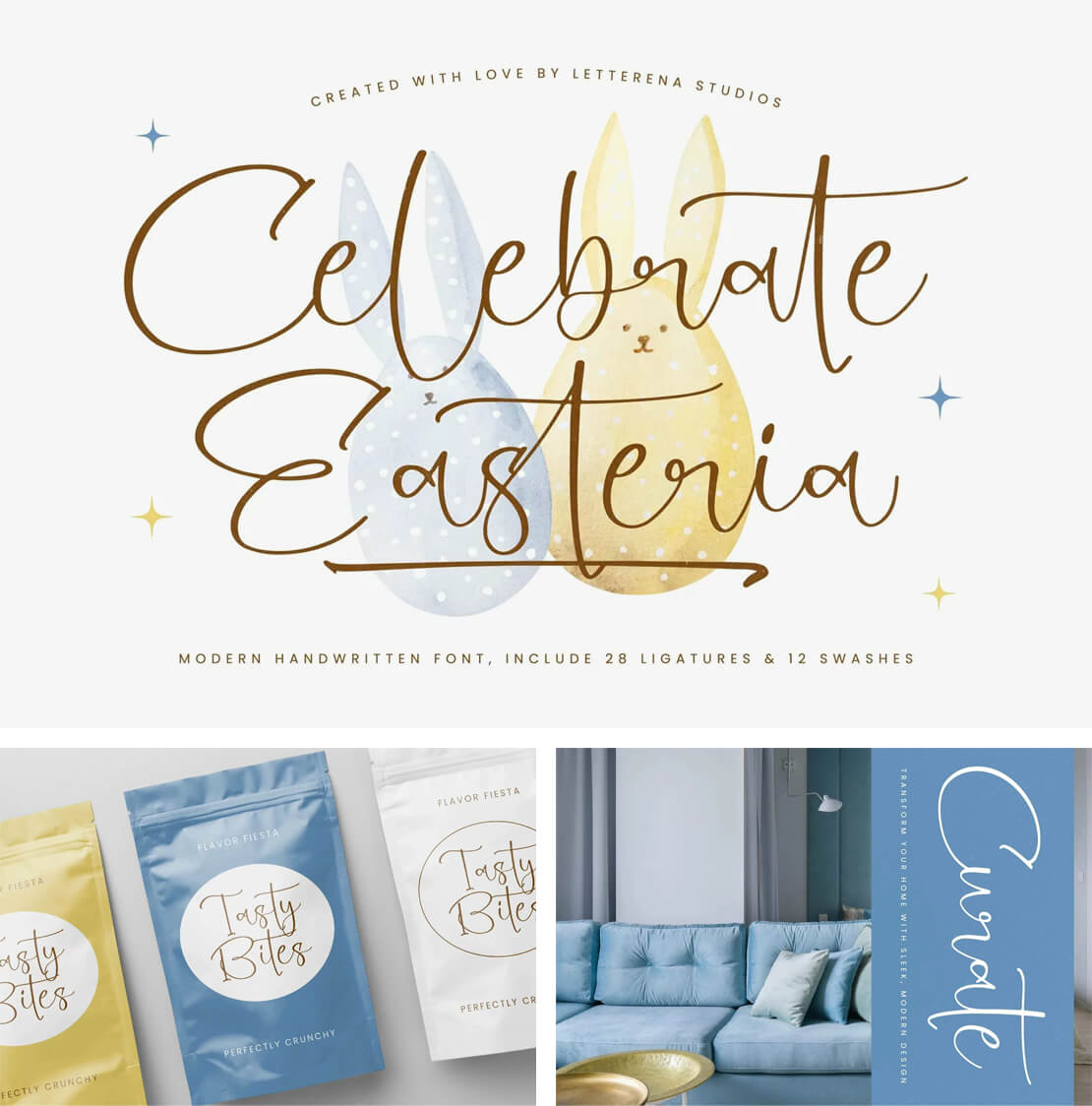
Celebrate Easteria
Eine moderne Schreibschrift mit elegantem, schwungvollem Charakter. »Celebrate Easteria« von Letterena steht kostenlos zum Herunterladen bereit.
Das Schriftbild von »Celebrate Easteria« zeichnet sich durch eine fließende Linienführung aus, die eine handgemachte Anmutung erzeugt. Die Script-Schrift bietet sich für vielfältige gestalterische Anwendungen a.
Um dem Textbild ein natürliches und abwechslungsreiches Aussehen zu verleihen, ist der Font technisch umfassend ausgebaut. Der Zeichensatz beinhaltet verschiedene Ligaturen, alternative Buchstabenformen sowie dekorative Schwünge (Swashes). Durch die PUA-Codierung (Private Use Area) lassen sich sämtliche Sonderzeichen auch in Standard-Programmen ohne erweiterte OpenType-Unterstützung unkompliziert abrufen.